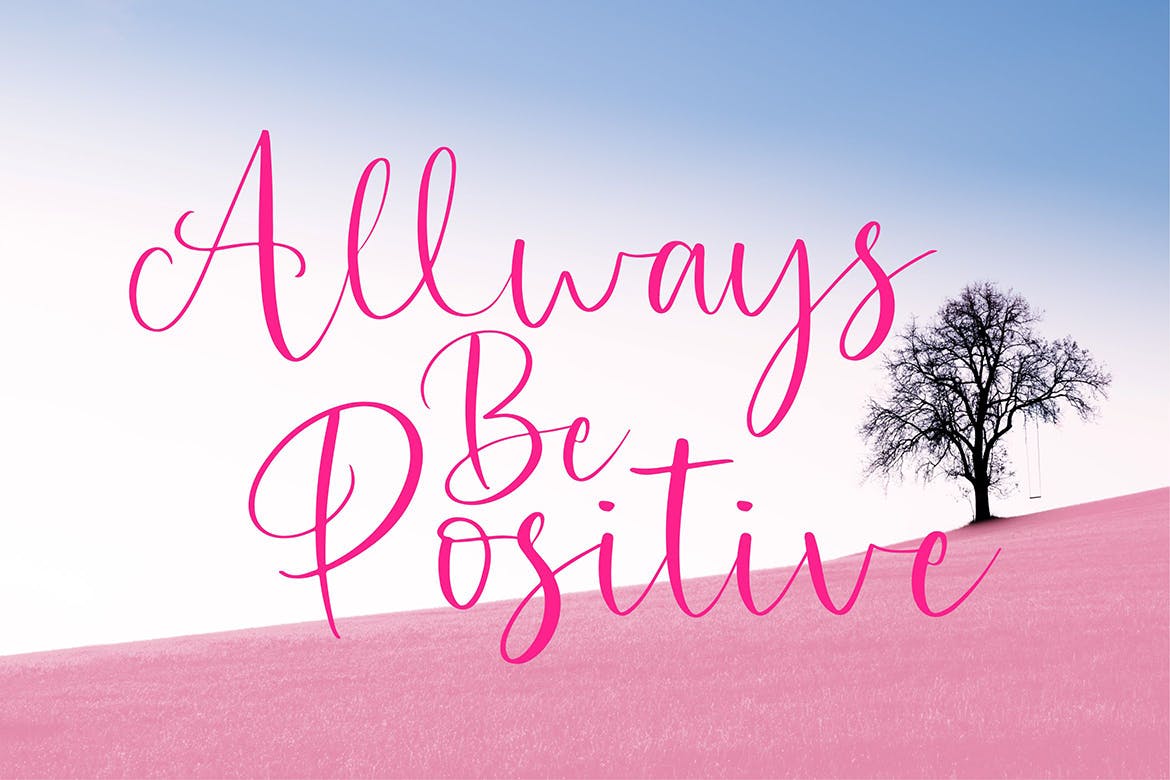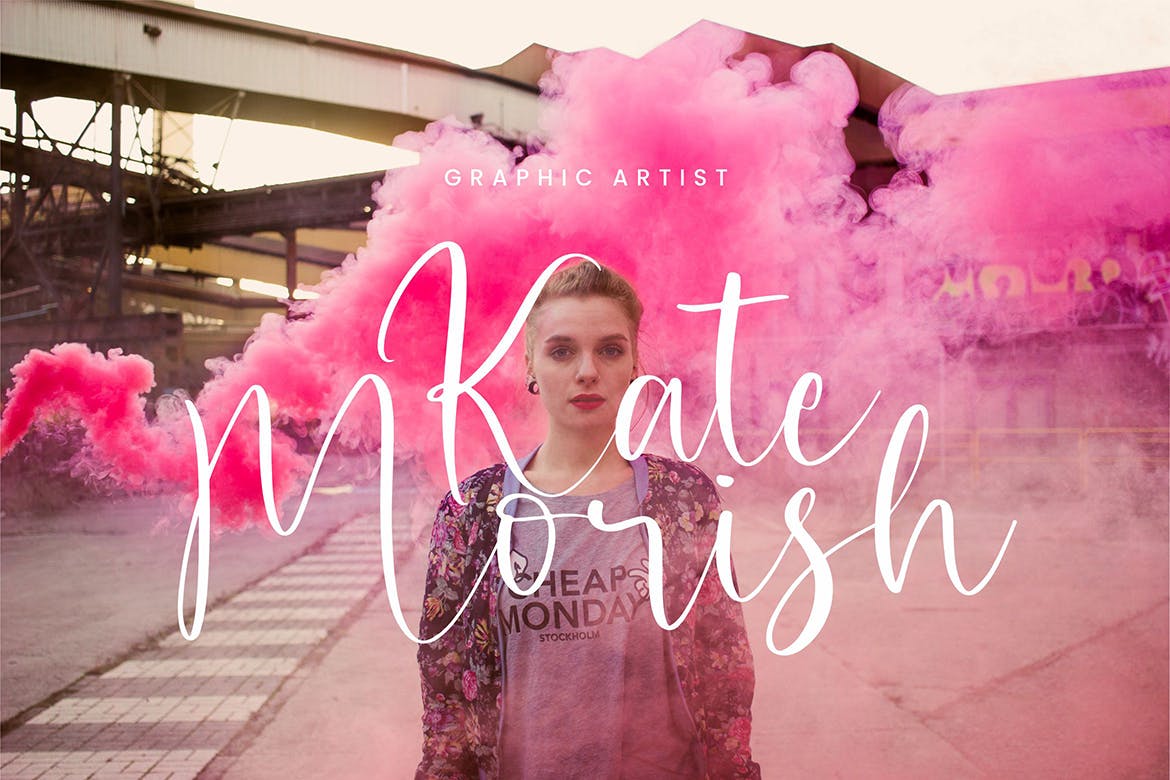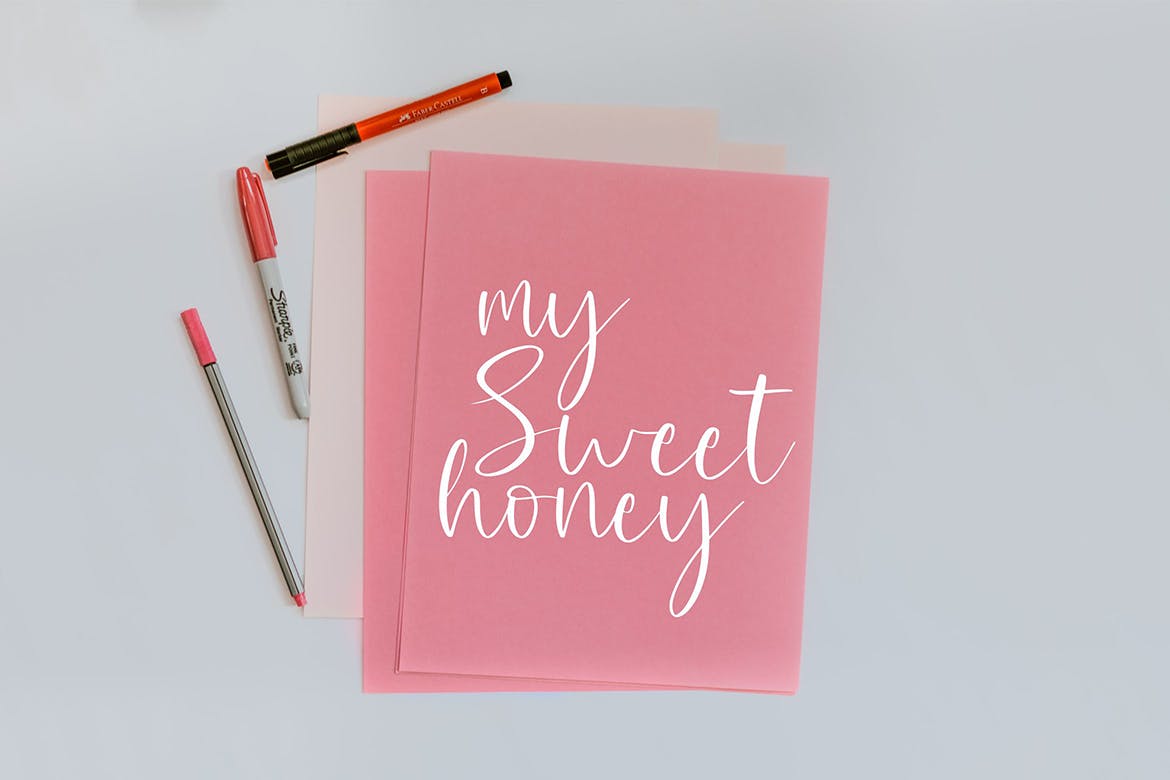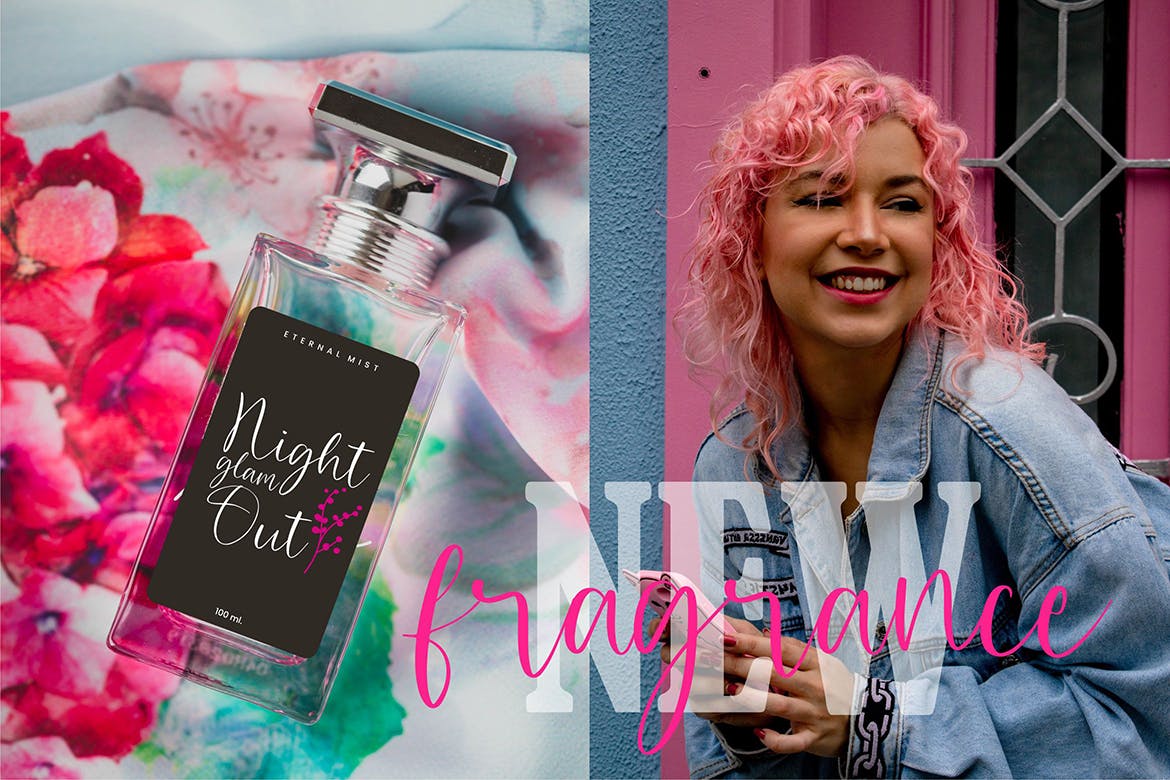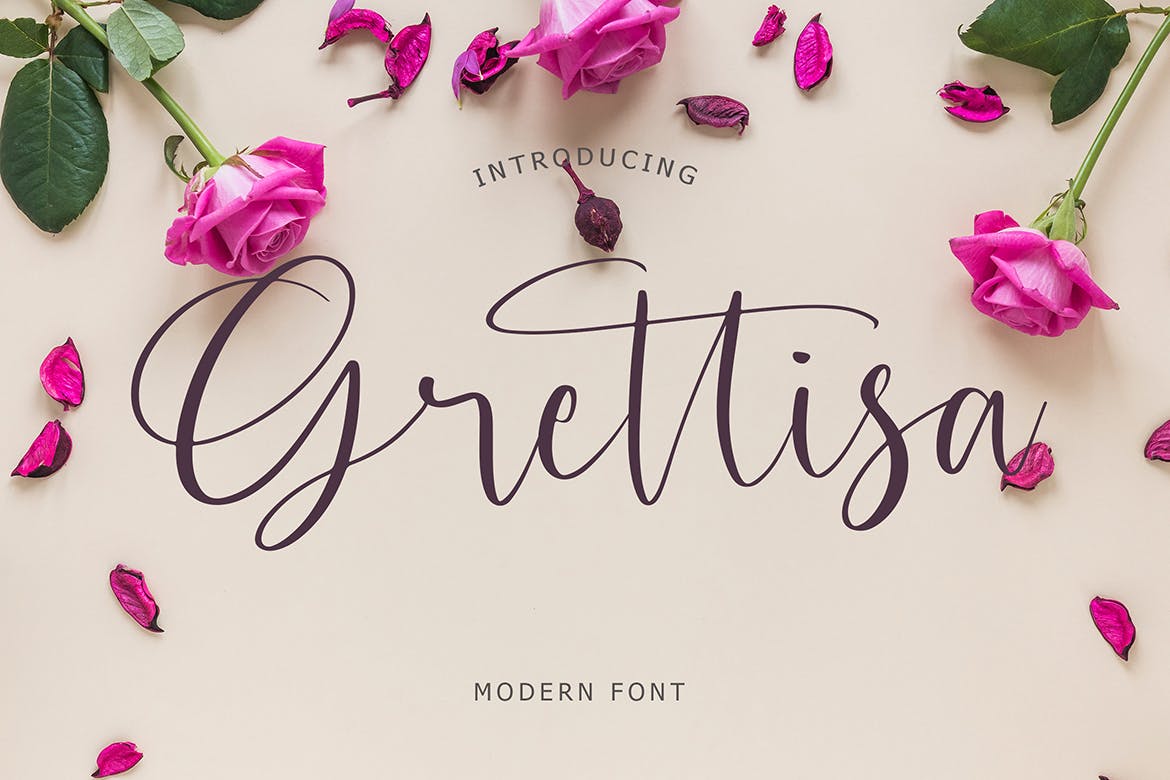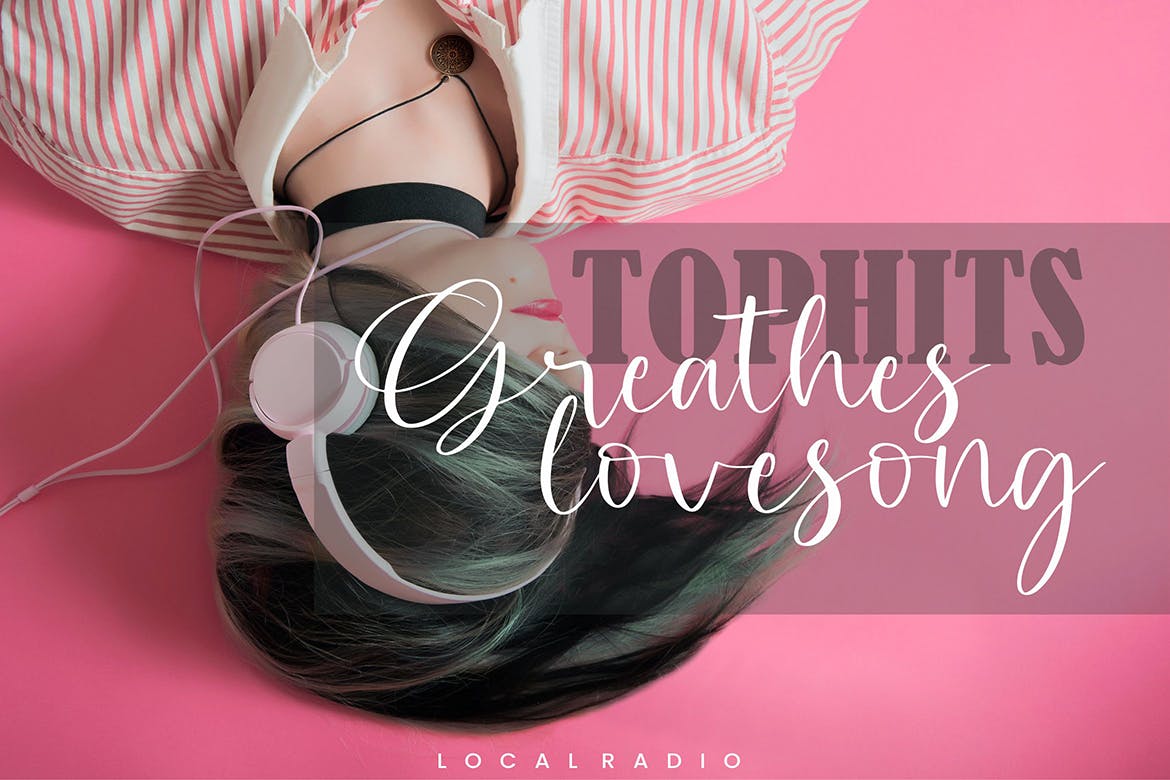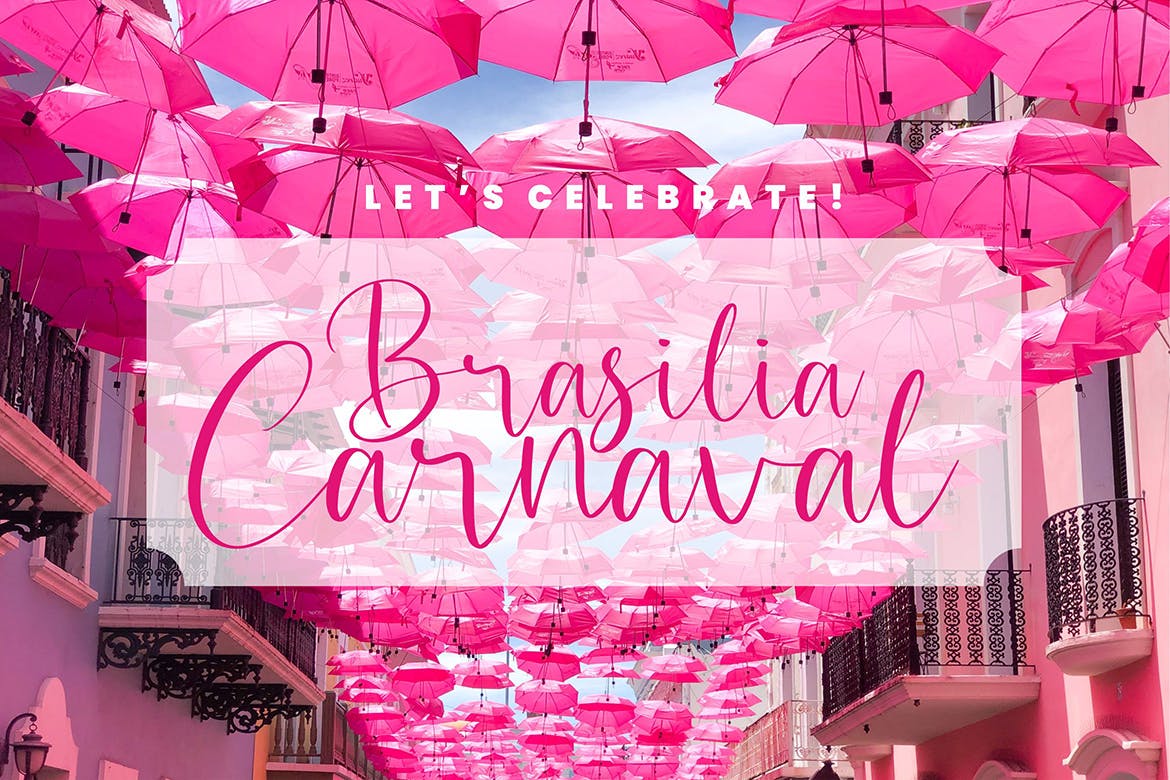
Grettisa یک فونت مدرن و دستنویس است که میتواند متن شما را با ظاهری شیک، لوکس و مدرن به نمایش بگذارد!
Grettisa برای پروژههای برندینگ، لوگو، طراحیهای عروسی، پستهای شبکههای اجتماعی، تبلیغات، بستهبندی محصولات، طراحی تیشرت، طراحی محصولات، برچسبها، عکاسی، واترمارک، دعوتنامه، لوازمالتحریر و هر پروژهای مناسب است.